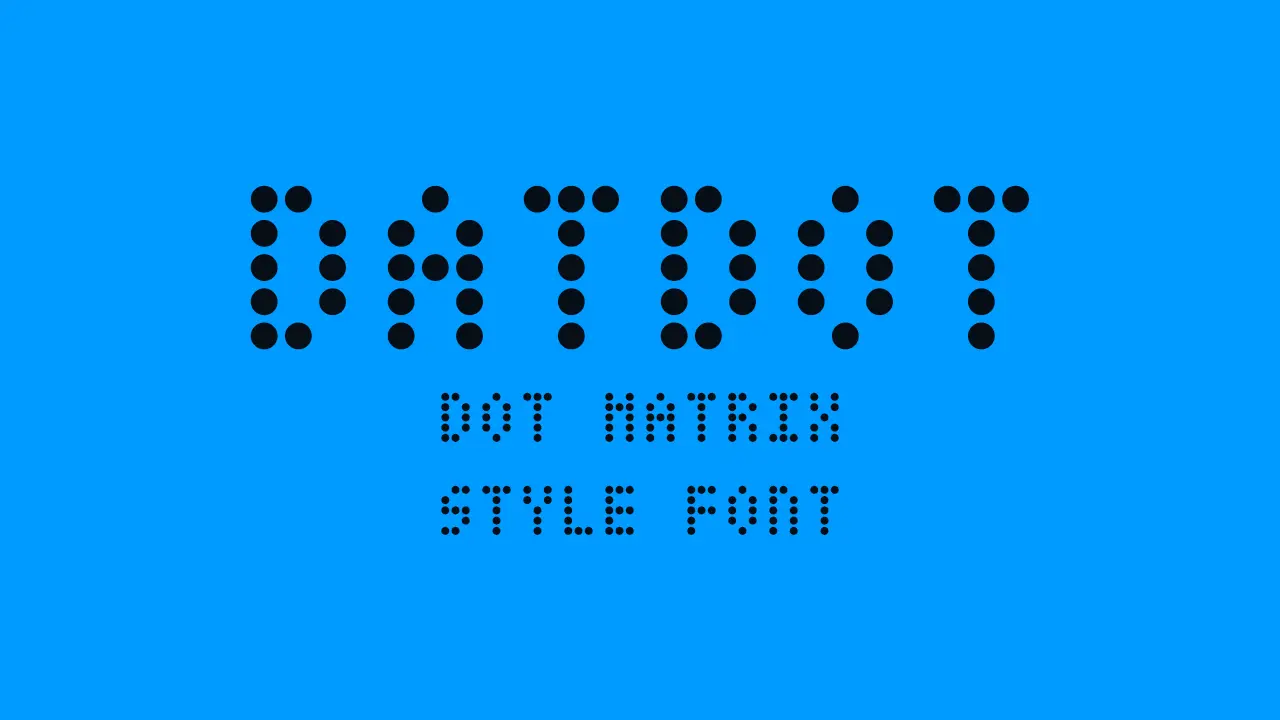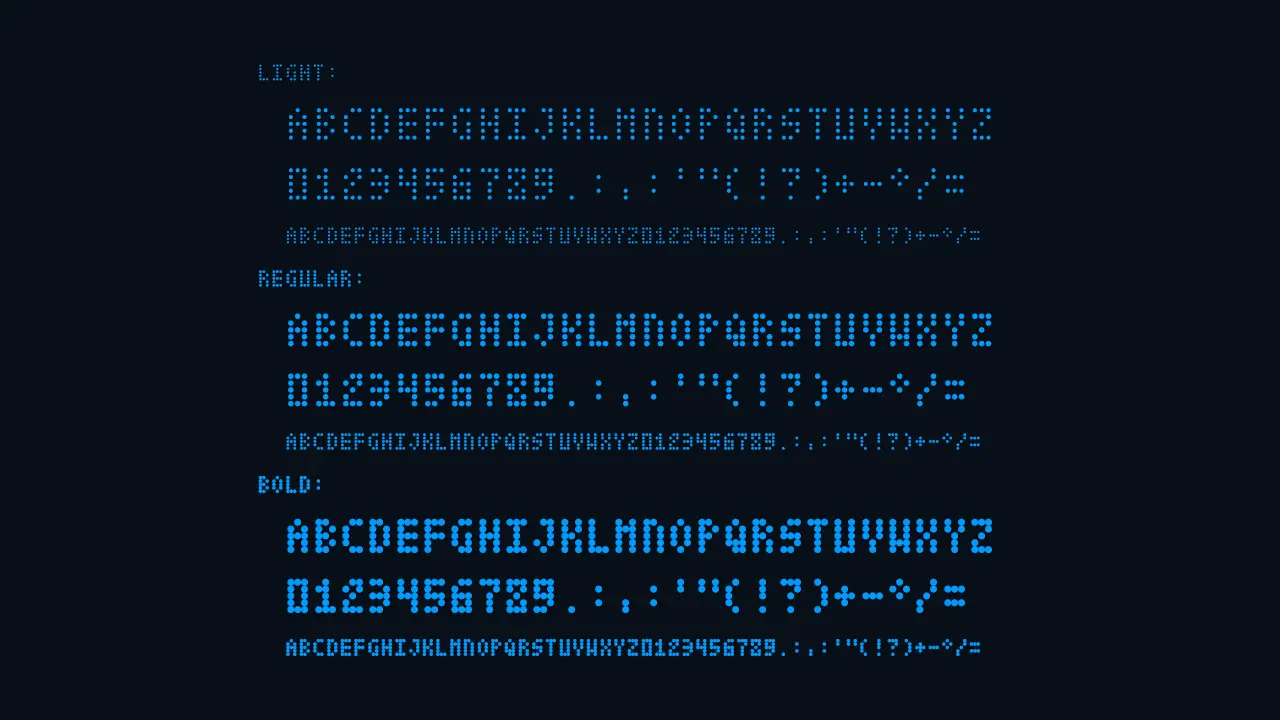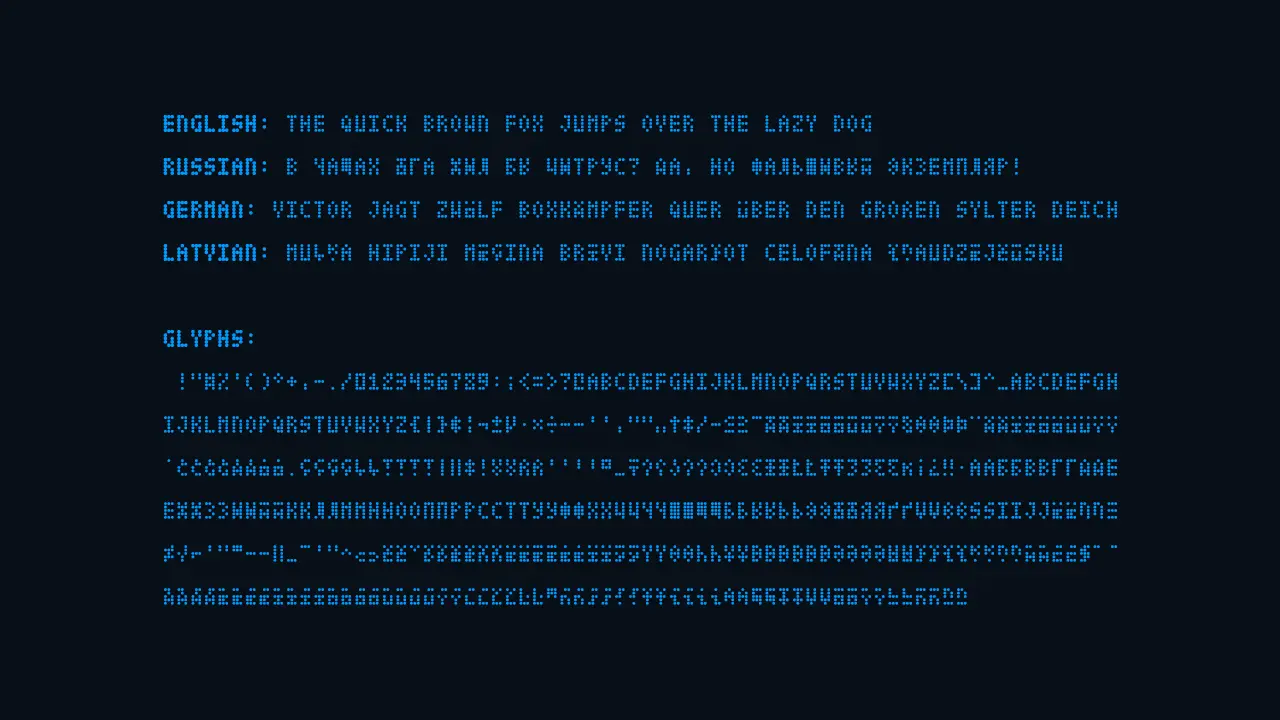
DatDot介紹
DatDot是一款圓形點陣樣式英文字體,根據SIL OFL協議發佈, 有3種樣式(Regular、Bold、Light)和 410個字形。
佈局網格 3x5(固定寬度和高度)。
支持 33 種語言(Aja, 阿爾巴尼亞語, 白俄羅斯語, 保加利亞語, 加泰羅尼亞語, 克羅地亞語, 達格巴尼語, 荷蘭語, 英語, 愛沙尼亞語, Fon, 德語, 印度尼西亞語, 意大利語, 拉丁語, 拉脫維亞語, 立陶宛語, 馬賽語, Mapudungun, 蒙古語, 北薩米語, 波蘭語, 俄語, 蘇格蘭蓋爾語,塞爾維亞語、斯洛文尼亞語、西班牙語、他加祿語、特拉帕內克語、烏克蘭語、烏茲別克語、西弗里斯蘭語、祖魯語。)